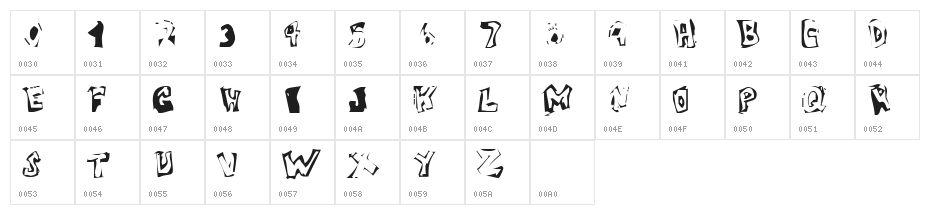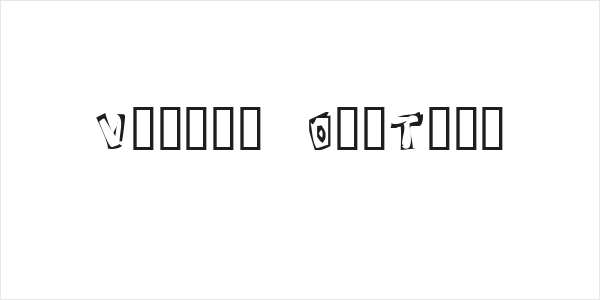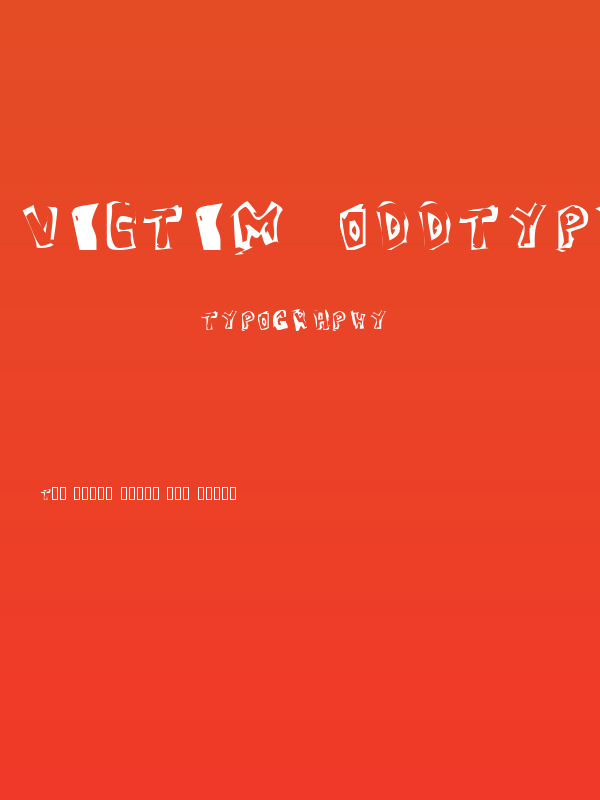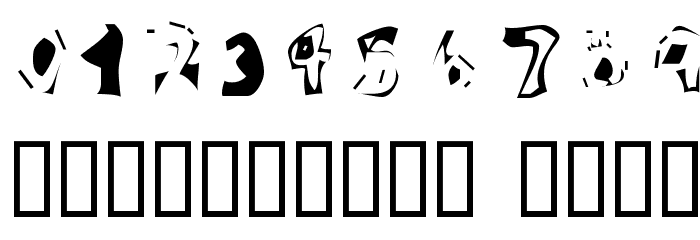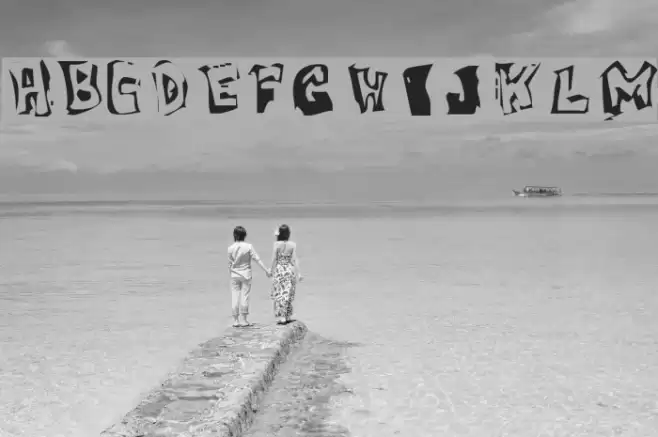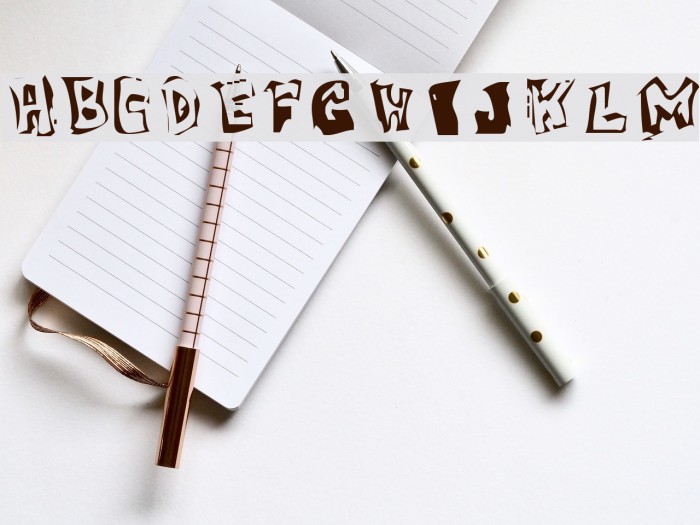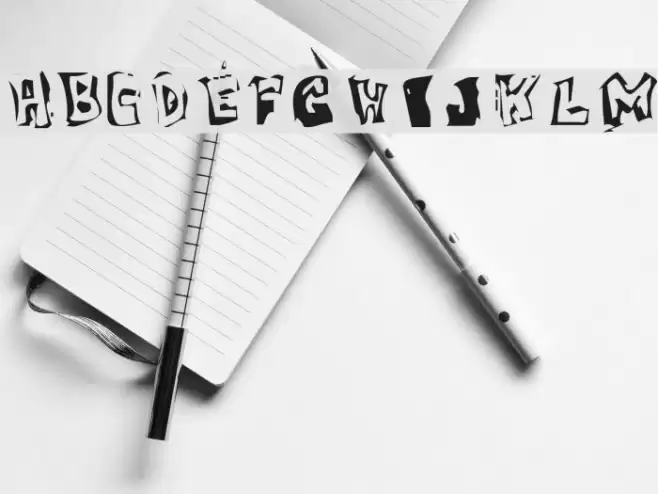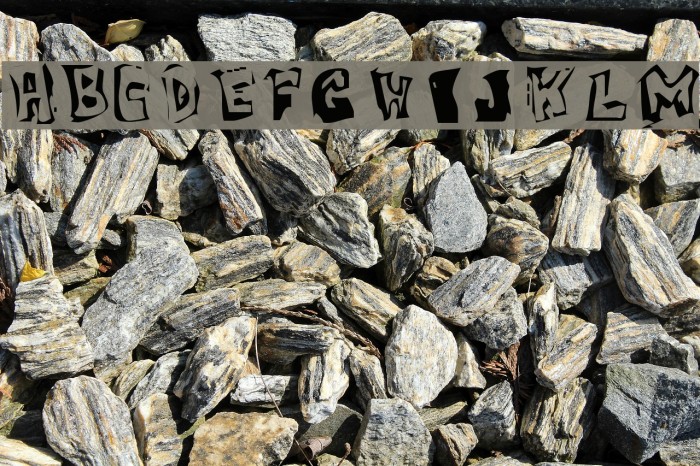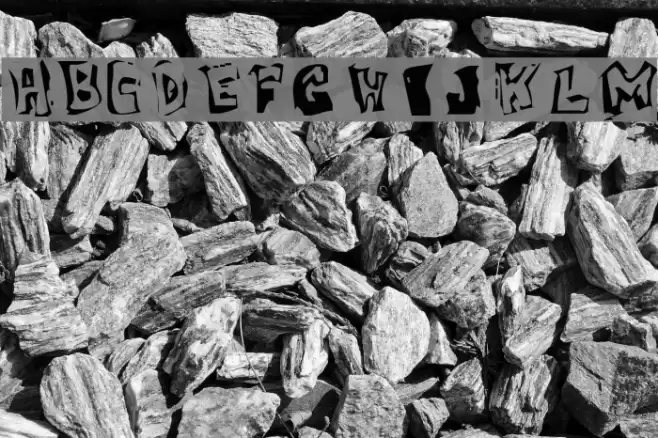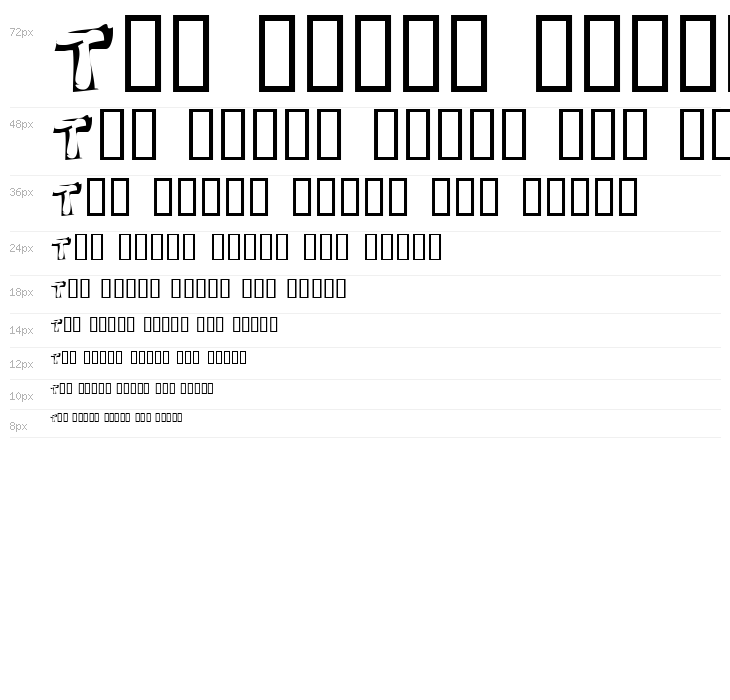
Victim OddType Font
| Catégories | Outline |
| Cas d'utilisation | Logos, Headlines |
| Projets proposés | Ideal for album covers, posters, and graphic design projects that require a bold and artistic touch. |